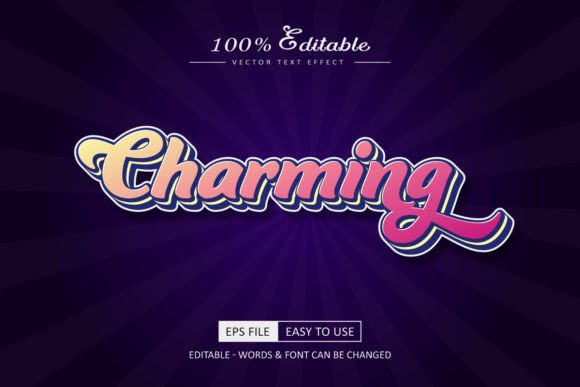
Charming Text Effect Font Style
Поиск подходящих элементов дизайна может быть сложным, но Charming Text Effect Font Style предлагает исключительную коллекцию, которая мгновенно улучшит вашу работу.
Созданный с высокой точностью, Charming Text Effect Font Style предоставляет чистые векторы, плавную типографику и коммерческую лицензию для вашего спокойствия.
Создаете ли вы продукты POD (печать по требованию), свадебные приглашения или графику для социальных сетей, Charming Text Effect Font Style станет идеальным выбором.